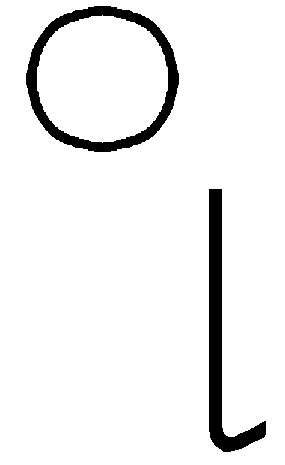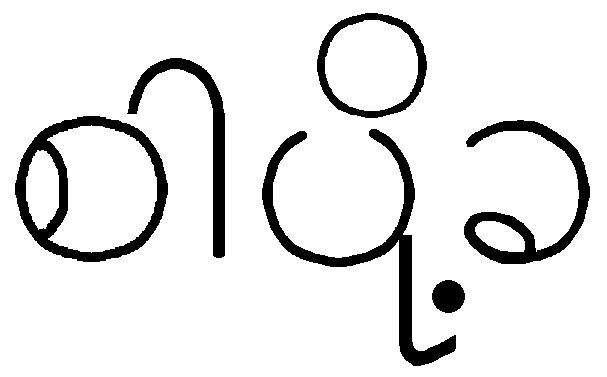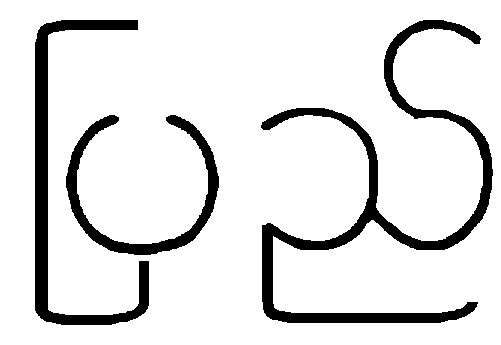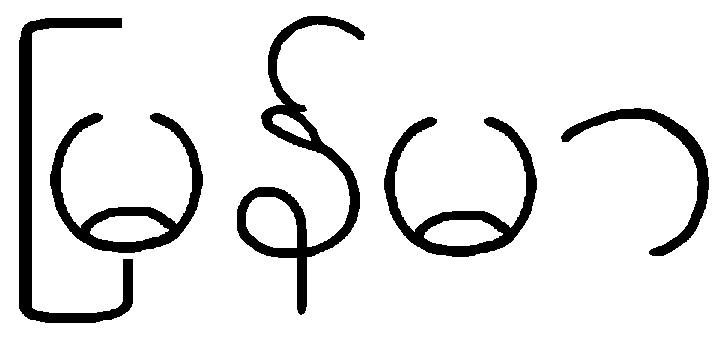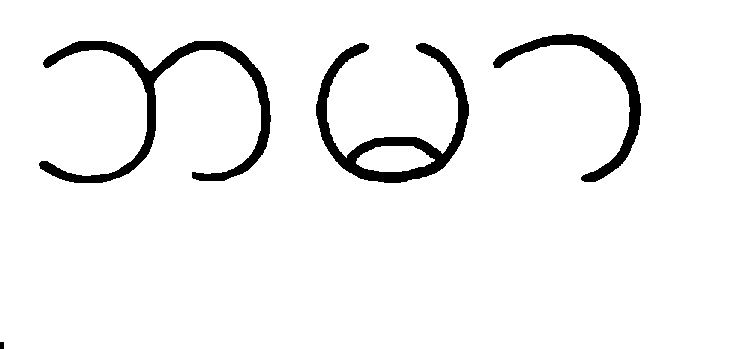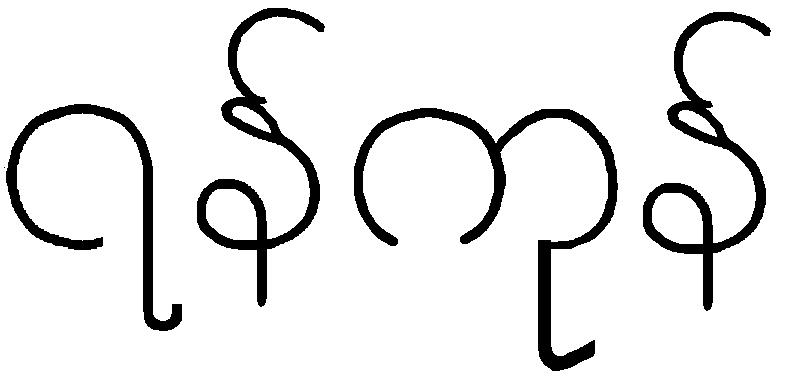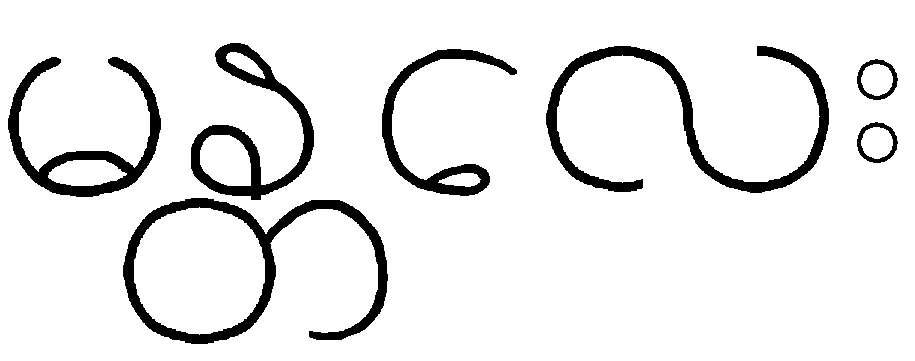
Die Staaten Burma, Kambodscha/Khmer, Thailand und Laos haben eigene Alphabete, die zur "Pali - Schriftengruppe" gehören. Es sind Silbenschriften.
Zeichensatz : Die burmesische Schrift kennt für Konsonanten 34 Groß- buchstaben und 9 Kleinbuchstaben; für Vokale ein "A" und 7 Zusatz- zeichen (mit Varianten). Dazu gibt es 3 Tonhöhenzeichen.
Konsonanten : von diesen Zeichen sind heute einige nicht mehr gebräuch- lich. Den Buchstaben hängt automatisch ein -a an, da die meisten Silben eben auf -a enden. Wenn eine Silbe nicht auf -a endet, muß ein Vokal- zeichen dazugesetzt werden. Die Aussprache weicht manchmal von der Schreibweise ab, wenn die Zeichen am Silbenende stehen.
Vokalzeichen schreibt man hinter, über, unter und sogar vor das Silbenzei- chen. Liest man also " ka " und " i " heißt es nicht " ka-i " , sondern " ki " !
Man unterscheidet nicht lange und kurze Vokale, jedoch gibt es unter- schiedliche Zeichen für Vokale in unterschiedlichen Tonhöhen.
Das burmesische Alphabet : a ) Großbuchstaben mit " -a"
| b) Kleinbuchstaben * auch : r | |||||||||||||||
| c) Vokale, die Ziffern bezeichnen die Tonhöhe | |||||||||||||||
d) Vokale am Anfang und am Ende von Silben (Beispiele) :
e) Tonhöhenzeichen :
f) Zahlenzeichen :
Schreibweise :
Der Unterschied zwischen "großen" und "kleinen" Buchstaben ist nicht, wie bei uns. Kleinbuchstaben verwendet man, wenn zwei Konsonanten aufein- ander folgen (siehe Khmer-Schrift). Auch der Unterschied zwischen Druck- schrift und Schreibschrift ist gering. Man schreibt von links nach rechts.
In Burma kennt man weder Komma noch Punkt. Wörter werden einfach hintereinander geschrieben, zwischen zwei Sätzen ist eine kleine Lücke.
Übersetzungen :